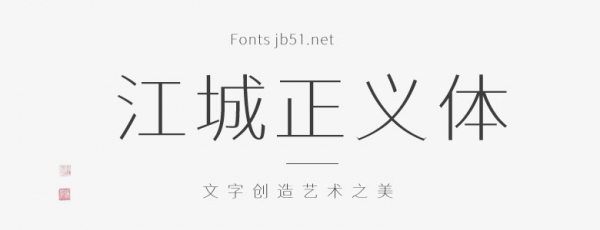
江城正義體是一款非常不錯的印刷字體,工整簡潔,具有強烈的視覺沖擊力,適應(yīng)于報紙和雜志和書籍中常用字體, 海報、個性促進品牌標志設(shè)計、字體設(shè)計、等環(huán)境使用,歡迎喜歡的朋友前來字體家下載使用。
江城正義體包含(200W/300W/400W/500W/600W)共五款字體。